Kurze Antwort: Öffne einen kostenlosen Schriftgenerator im Browser, gib deinen Text in das Eingabefeld ein, wähle einen Schriftstil aus der Liste und klicke auf „Kopieren“. Dann fügst du den Text ganz normal per Strg+V (oder Cmd+V auf dem Mac) überall ein – bei Instagram, WhatsApp, TikTok oder wo auch immer du willst. Keine Installation, keine Anmeldung, kein Aufwand.
Du hast bestimmt schon mal einen Post bei Instagram oder WhatsApp gesehen, bei dem der Text in einer total verrückten oder eleganten Schrift geschrieben war – und dich gefragt: Wie macht der das? Die Antwort ist einfacher als du denkst: Ein Schriftgenerator macht genau das möglich, und zwar in wenigen Sekunden, kostenlos und ohne jede App-Installation.
In diesem Artikel erkläre ich dir, was ein Schriftgenerator ist, wie du ihn Schritt für Schritt nutzt und wofür er sich am besten eignet.
Was ist überhaupt ein Schriftgenerator?
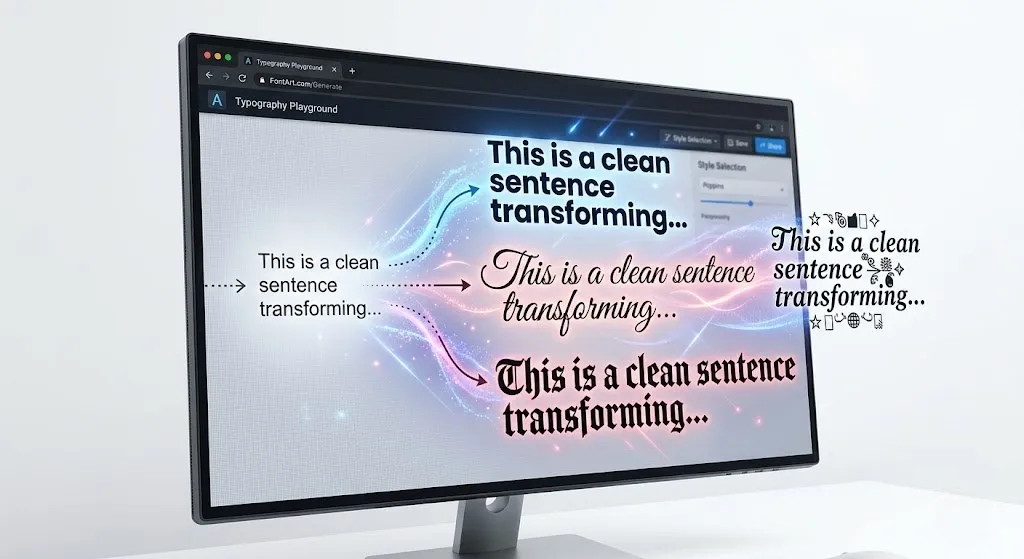
Ein Schriftgenerator ist ein Online-Tool, mit dem du gewöhnlichen Text in verschiedene Schriftstile umwandeln kannst. Du gibst deinen Text ein – und sofort siehst du ihn in vielen verschiedenen Variationen: kursiv, fett, verschnörkelt, mit Sonderzeichen, wie Kursivschrift aus einem Fantasy-Buch oder sogar als Geheimschrift.
Das Besondere dabei: Die meisten dieser Schriften funktionieren über sogenannte Unicode-Zeichen. Das sind besondere Sonderzeichen, die in fast jedem Gerät und fast jeder Plattform schon eingebaut sind. Deshalb musst du keine Schriftart herunterladen oder installieren – du kopierst einfach den fertigen Text und fügst ihn ein, wo immer du willst. Für weitere Details kannst du auch unseren Artikel über was ein Schriftgenerator ist lesen.
Wozu brauche ich einen Schriftgenerator?
Die einfache Antwort: überall dort, wo du mit deinem Text auffallen willst. Hier ein paar typische Anwendungsbereiche:
- Instagram-Bio und Posts: Eine ausgefallene Schrift in deinem Profil zieht sofort Blicke auf sich.
- WhatsApp-Nachrichten: Überrasch deine Freunde mit einer Nachricht in verrückter Schrift.
- TikTok-Beschreibungen: Auch auf TikTok lassen sich solche Schriften problemlos einfügen.
- Facebook-Posts und -Kommentare: Wer viel auf Facebook unterwegs ist, kann sich mit besonderen Schriften von der Masse abheben.
- Einladungen und Karten: Für Geburtstags- oder Hochzeitseinladungen lassen sich schöne Schriftzüge als Bild herunterladen.
- Übungsvorlagen für Handlettering: Viele Menschen nutzen Schriftgeneratoren, um Vorlagen zum Nachzeichnen auszudrucken.
Schritt-für-Schritt-Anleitung: So benutzt du einen Schriftgenerator
Die Nutzung ist wirklich simpel. Hier eine Schritt-für-Schritt-Erklärung, die für die meisten kostenlosen Online-Schriftgeneratoren gilt:
Schritt 1: Schriftgenerator im Browser öffnen
Gehe einfach in deinem Browser (Chrome, Firefox, Edge oder Safari) auf eine Schriftgenerator-Website deiner Wahl. Du brauchst nichts zu installieren – das Tool läuft direkt im Browser. Achte darauf, einen aktuellen Browser zu verwenden, damit alle Funktionen einwandfrei klappen.
Schritt 2: Deinen Text eingeben
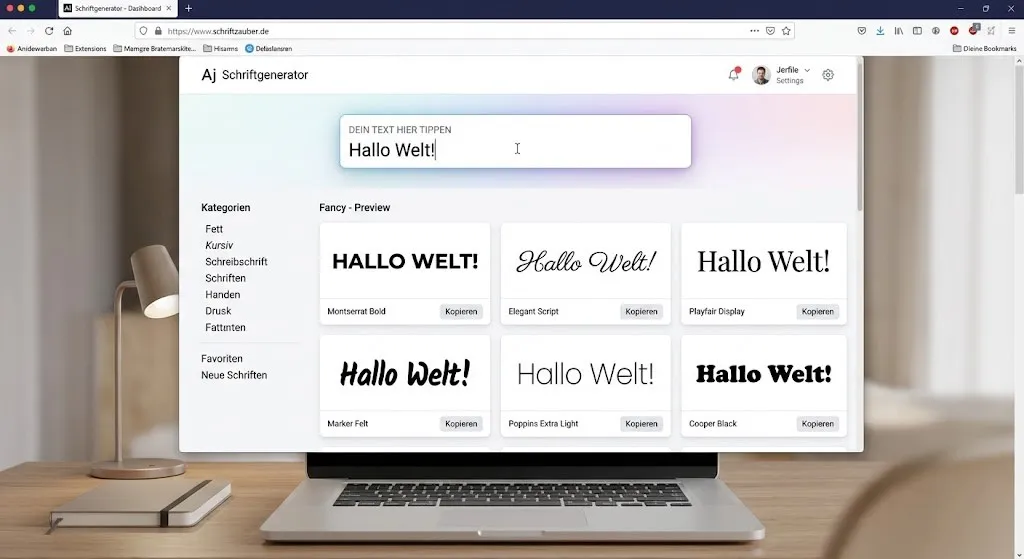
Du siehst ein Eingabefeld. Schreibe dort einfach deinen gewünschten Text hinein – einen Namen, einen Spruch, einen kurzen Satz oder was auch immer du brauchst. Manche Tools zeigen dir das Ergebnis in Echtzeit direkt während der Eingabe, ohne dass du auf einen Button klicken musst.
Schritt 3: Schriftstil auswählen
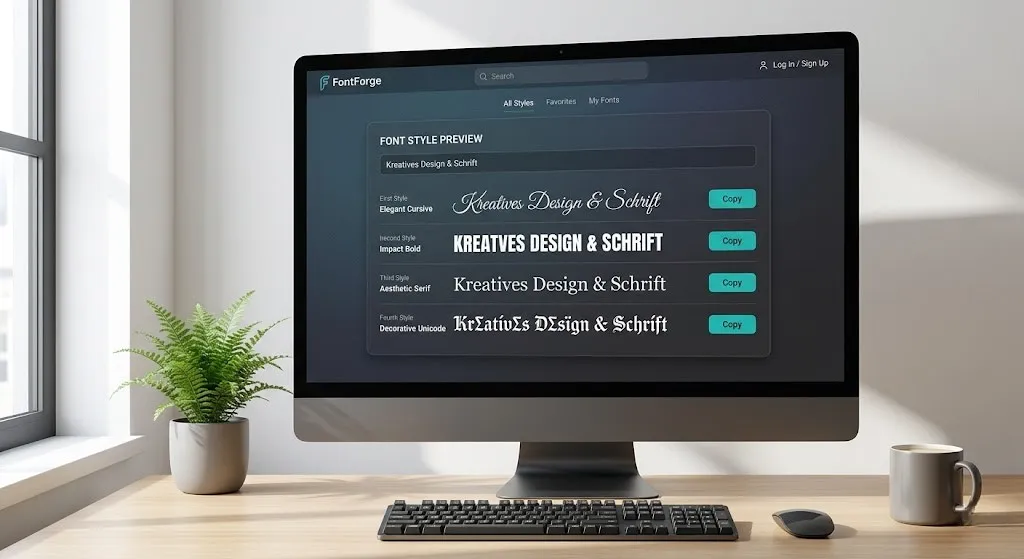
Unterhalb des Eingabefeldes erscheint dein Text automatisch in vielen verschiedenen Schriftstilen. Je nach Tool stehen dir dabei unterschiedliche Kategorien zur Verfügung:
- Schriften zum Kopieren (als Text): Diese basieren auf Unicode-Zeichen und lassen sich direkt in soziale Netzwerke, Messenger oder andere Texteingabefelder einfügen.
- Schriften als Bild: Diese werden als PNG oder JPG generiert und können heruntergeladen werden – ideal für Canva, PowerPoint, Google Docs oder den Druck.
Schau dir die verschiedenen Varianten in Ruhe an. Meist gibt es ein Symbol oder einen kleinen Button direkt neben jeder Schrift, mit dem du sie in die Zwischenablage kopierst.
Schritt 4: Text kopieren und einfügen
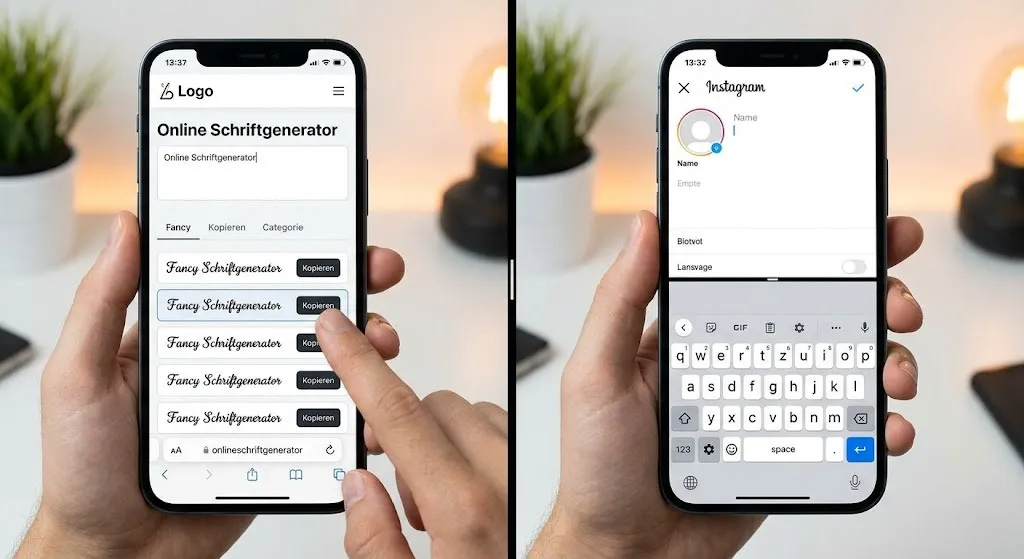
Klicke auf das Kopier-Symbol neben dem gewünschten Schriftstil. Der Text landet automatisch in deiner Zwischenablage. Gehe dann zur App oder Plattform deiner Wahl (Instagram, WhatsApp, TikTok, etc.) und füge den Text einfach mit Strg+V (Windows) oder Cmd+V (Mac) ein – fertig.
Schritt 5 (optional): Schrift als Bild speichern
Wenn du die Schrift als Grafikdatei brauchst, kannst du bei vielen Generatoren auch ein Bild herunterladen. Das ist praktisch, wenn du die Schrift in ein Design einbauen willst, zum Beispiel auf einer Einladungskarte, einem Plakat oder in einer Präsentation. Die Dateien liegen meistens als transparentes PNG vor, damit du sie flexibel weiternutzen kannst.
Tipps für bessere Ergebnisse
Ein paar kleine Hinweise, die den Unterschied machen:
Funktioniert ein Schriftgenerator auch auf dem Handy? Ja, die meisten Schriftgeneratoren sind für den mobilen Einsatz optimiert und laufen im mobilen Browser genauso gut wie am Desktop.
Ein Schriftgenerator ist eines dieser Tools, das unglaublich einfach klingt – und dann im Alltag deutlich nützlicher ist, als man zunächst denkt. Probier es einfach aus. Du wirst überrascht sein, wie viel ein bisschen Typografie ausmachen kann.